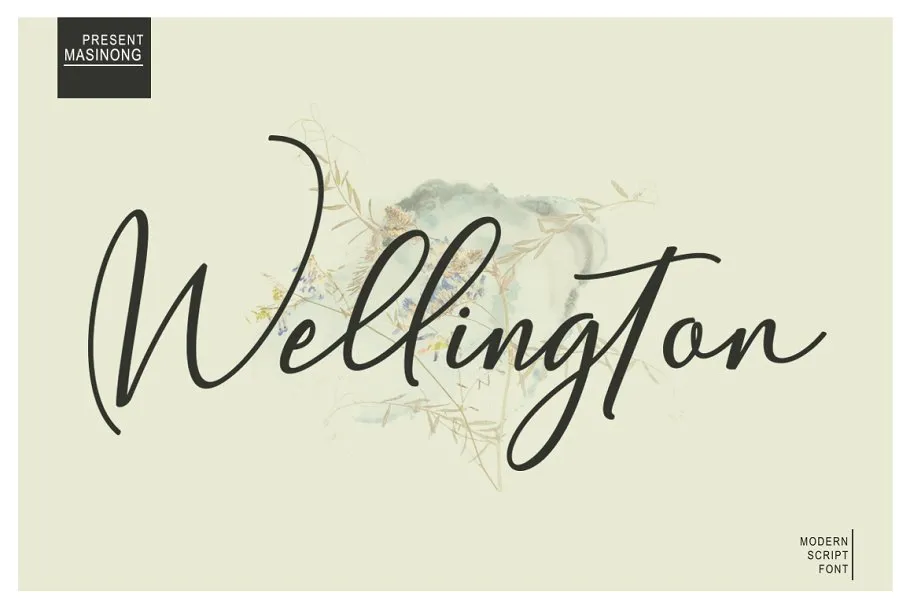
Wellington Calligraphy Font – Download Grátis
A nova Wellington Calligraphy Font é uma deliciosa mistura de estilo moderno e arte handmade que traz a beleza autêntica do desenho manual ao seu design digital. Ideal para qualquer projeto, esta tipografia script moderna foi projetada pelo designer Hamilton para ser perfeita em criações de logos, imagens de marca, citações escritas à mão, embalagens de produtos e até mesmo postagem nas redes sociais. Com Wellington, é simples e prazeroso criar letras únicas apenas digitando seus textos. A fonte adiciona um toque atrativo aos seu projetos, garantindo um visual atraente e único. Estou preparado para experimentar esta nova adição à sua biblioteca de tipos?